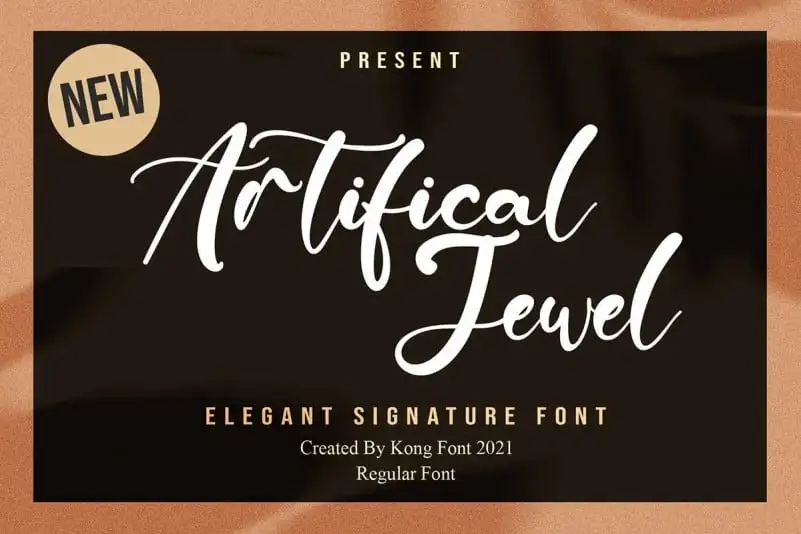
Artificial Jewel Script Font – Download Grátis
A Artificial Jewel Script Font é uma elegante tipografia de script criada pela Kong Font com um toque nostálgico e linhas de traço que destacam uma alta contraste entre os elementos círconflexuais. Este tipo é perfeito para o design de logotipos, títulos de filmes ou livros, bem como qualquer projeto incrível que você possa criar. Com apenas um simples toque da Artificial Jewel Font Flurry, você pode produzir trabalhos que se destacam e fazem seu conteúdo brilhar com sua arte gráfica única. Experimente esta fonte elegante para adicionar uma pitada de luxo ao seu próximo projeto visual.